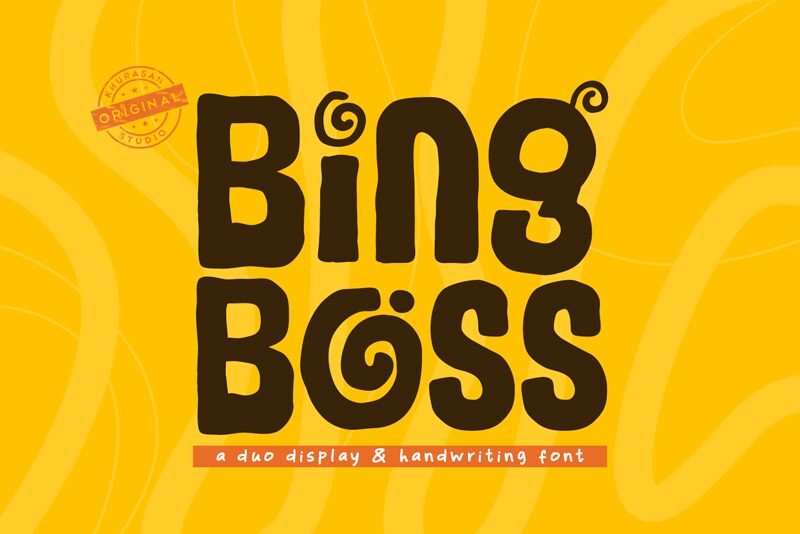
Bing Boss di Khurasan è un carattere display cartoon gratuito, con lettere robuste e irregolari e una vivace silhouette disegnata a mano. Piccoli dettagli a spirale ne accentuano l'estroso carattere da fumetto.
Le copertine dei libri per bambini sono un contesto particolarmente convincente, poiché le forme ampie ricordano le scritte disegnate per i titoli di testa animati. La stessa allegra irregolarità si adatta alle confezioni di giocattoli, ai poster per feste e al branding informale nel settore alimentare. In tutti questi ambiti, le forme arrotondate e i dettagli arricciati collegano le parole a un'illustrazione giocosa.